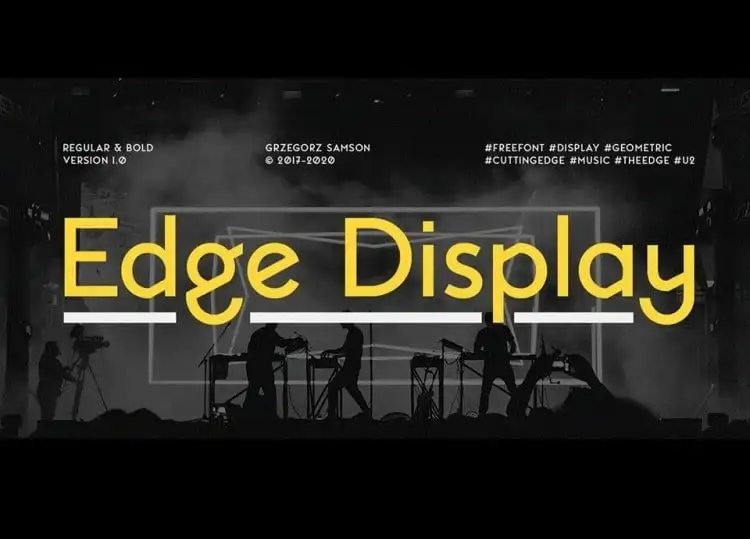
Edge Display Font – Download Grátis
Edge Display Font é uma tipografia sans-serif criada para entregar seu mensagem de forma poderosa e clara. Este tipo de letra geométrica foi desenvolvida por Grzegorz Samson, incluindo pesos Regular e Bold. Inspirado no álbum “The Edge” da banda U2, esta fonte perfeita para aplicar em materiais relacionados à música como posteres, logos de bandas e muito mais. Ideal tanto para designers gráficos quanto para quem busca um estilo minimalista e moderno para suas criações visuais.